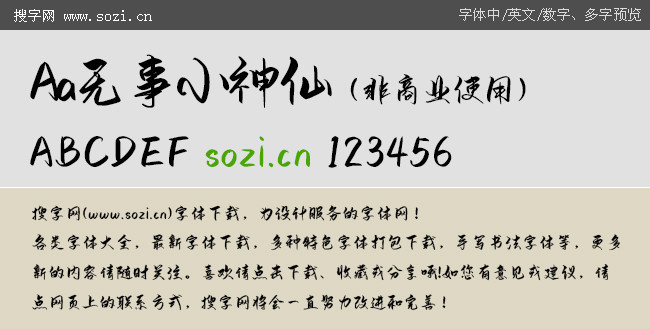
Aa無事小神仙
搜字網(wǎng)給大家提供一款Aa無事小神仙(非商業(yè)使用)中文字體下載,該字體是一款手寫字體,字體書寫流暢,字形隨性灑脫,具有很好的視覺感,適用于平面宣傳設計、網(wǎng)頁設計、海報設計等應用(此字體為個人非商用版,商用可以聯(lián)系QQ:1006760504)。